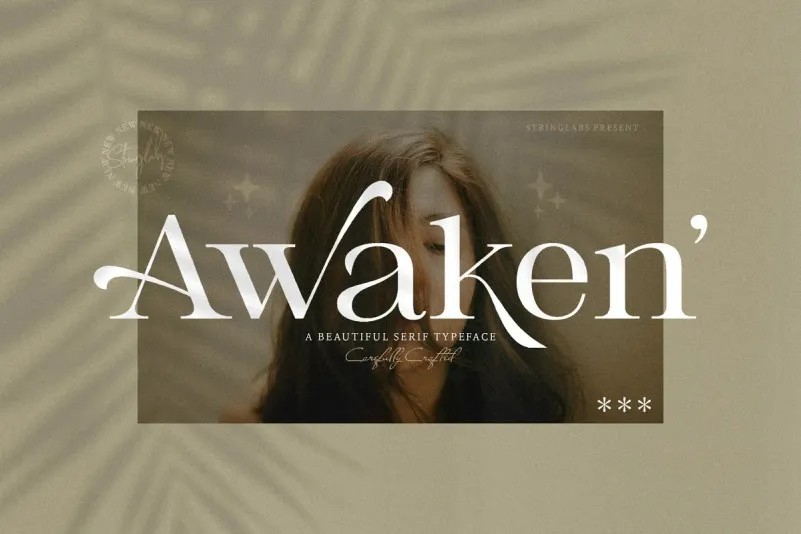
Awaken Serif Font – Fonte Grátis
Awaken Serif Font
A fonte ‘Awaken Serif Font’ é uma escolha perfeita para quem busca elegância com personalidade. Criada pela StringLabs, essa serif font apresenta detalhes distintos e interessantes, incluindo caudas únicas, alternativas de linhas e ornamentações extras. Seus traços são tão versáteis que se adaptam a uma ampla gama de projetos, tornando-a um recurso valioso para designers criativos em busca de algo inovador. Adicione essa fonte às suas ideias futuras e admire como ela as destaca, deixando-as ainda mais irresistíveis e singulares. Ideal tanto para design editorial quanto para logotipos ou texturas gráficas, a ‘Awaken Serif Font’ é uma escolha perfeita para aqueles que desejam dar um toque único às suas criações.